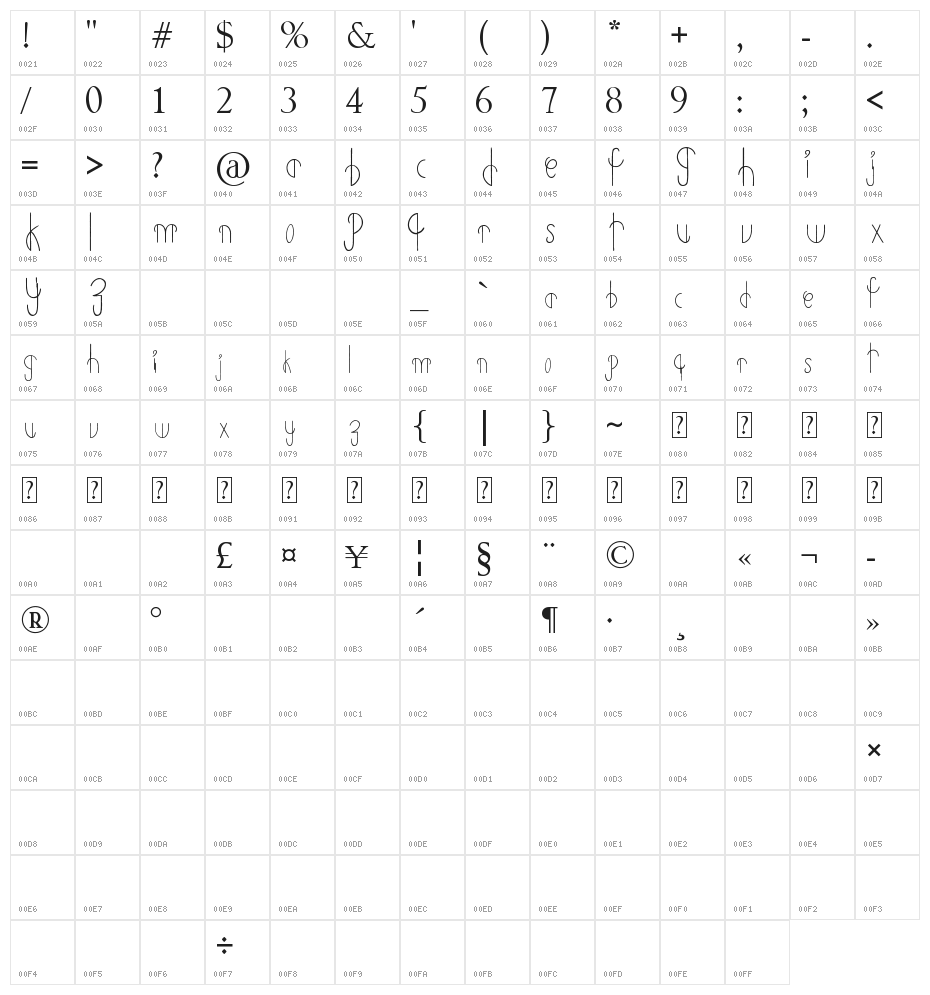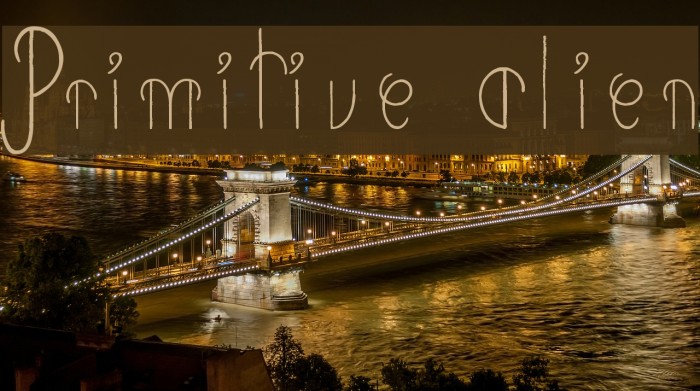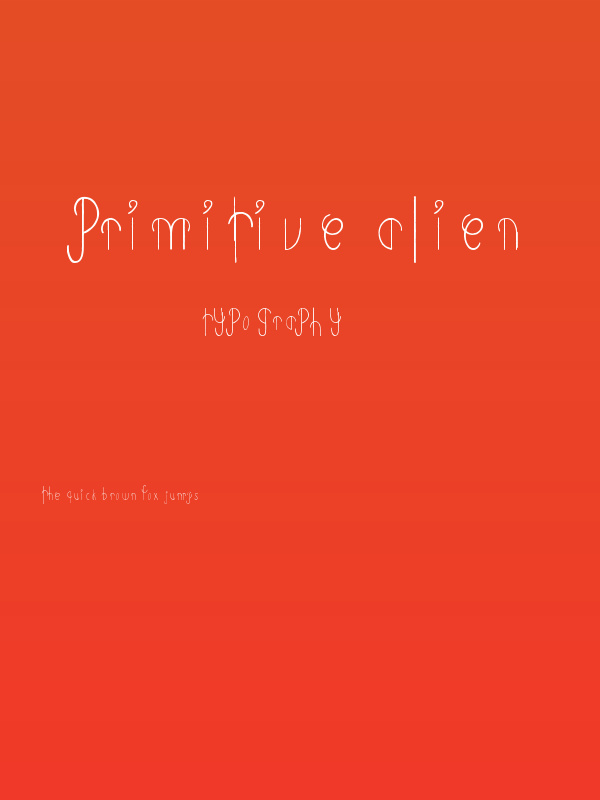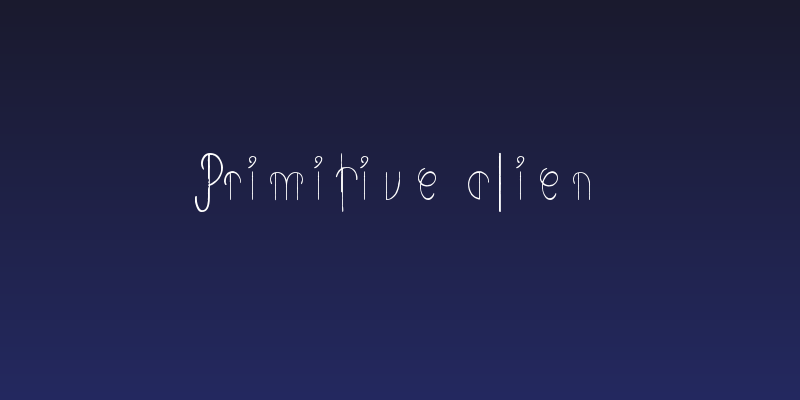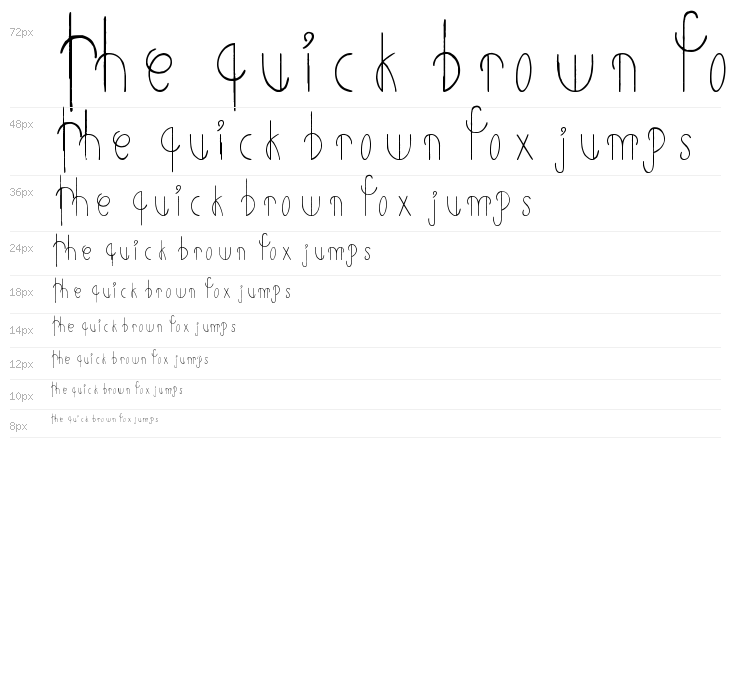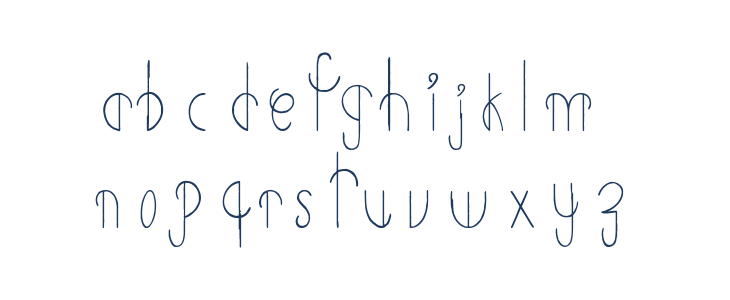
Primitive Alien Font
| Vorgeschlagene Projekte | Ideal for creative projects such as posters, album covers, or branding that seeks a unique and artistic flair. |